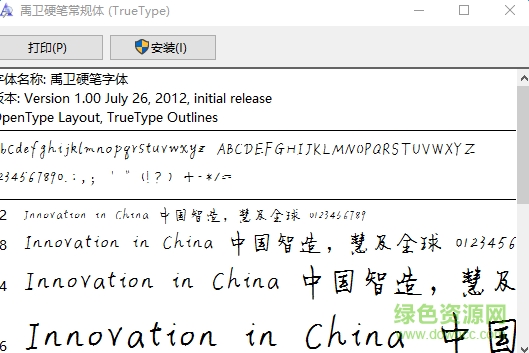
禹衛(wèi)硬筆字體是禹衛(wèi)字庫中的一款很有個性的電腦硬筆字體,這款字體不像普通的字體那樣呆板,它是比較活潑有特色的,用于藝術(shù)設(shè)計、廣告設(shè)計等方面都是沒有問題的,有需要的朋友可以來綠色資源網(wǎng)下載。
禹衛(wèi)硬筆字體是一款獨(dú)特的電腦字體,字體線條柔和,筆畫靈活,寫出來的效果很不錯,優(yōu)雅而又不失個性,喜歡的朋友就來綠色資源網(wǎng)下載吧。
《禹衛(wèi)字體》系列是國內(nèi)知名文字創(chuàng)意人禹衛(wèi)先生所開發(fā)制作,自2012年以來,相繼開發(fā)制作出《禹衛(wèi)硬筆常規(guī)體》、《禹衛(wèi)書法行書體》、《禹衛(wèi)書法隸書體》,這些字體均是GB_2312字庫,均包含了常用字和生僻字,其中后兩種字體是分為簡、繁兩套字體,廣泛適用于微軟office的各種軟件、qq、MSN等常用聊天工具、photoshop等主流繪圖軟件。